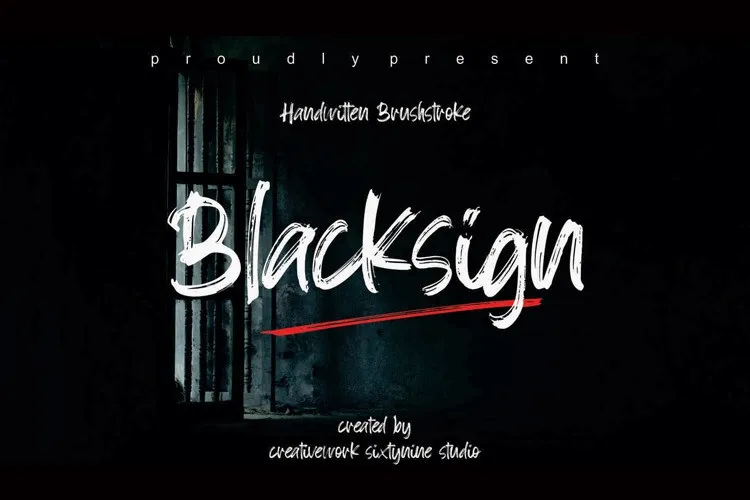
Esta é uma fonte desenhada com um estilo natural de pincel e textura única que pode melhorar a qualidade dos seus projetos. Seja para ilustrações, logotipos ou qualquer outro tipo de criação visual, esta fonte se destacará no seu banco de fonts. Ela traz uma qualidade impressionante para qualquer trabalho, potencializando-o em um nível elevado, independentemente do tópico. Este é um ativo valioso para qualquer designer gráfico que busca inovação e originalidade. Seja você especialista ou iniciante, a ‘Blacksign Font’ pode revolucionar a maneira como você visualiza seu design. Experimente-a agora e veja o impacto real desta font de pincel natural em suas próximas criações!